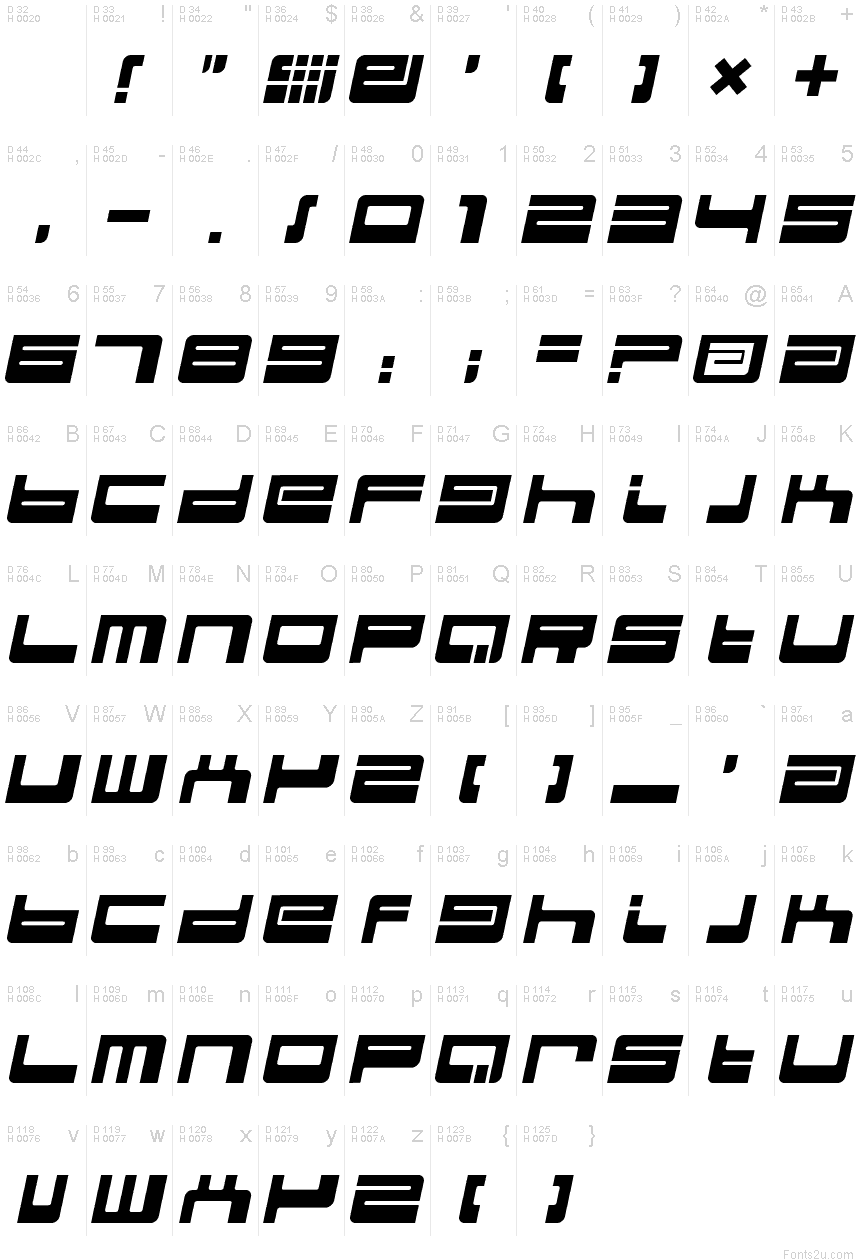
BD Eject Italic di M. Brunner e Lopetz98 di buro destruct è un font display futurista gratuito composto da tratti ampi e inclinati e forme geometriche tagliate di netto. Le sue lettere combinano lunghe barre orizzontali con angoli bruschi e spazi aperti, producendo una silhouette tecnica e veloce dall'aspetto tipico della grafica elettronica della fine degli anni Novanta.
I titoli per interfacce digitali sono il suo impiego principale, in particolare per i giochi e il branding tecnologico che possono richiamare la struttura segmentata del font. Si legge come l'etichetta di un'interfaccia personalizzata. Anche le copertine di album e i poster di eventi possono sfruttare la sua aggressiva spinta in avanti, e si rivolgerà in modo più diretto a un pubblico familiare con le immagini dei giochi arcade e la cultura elettronica sperimentale.